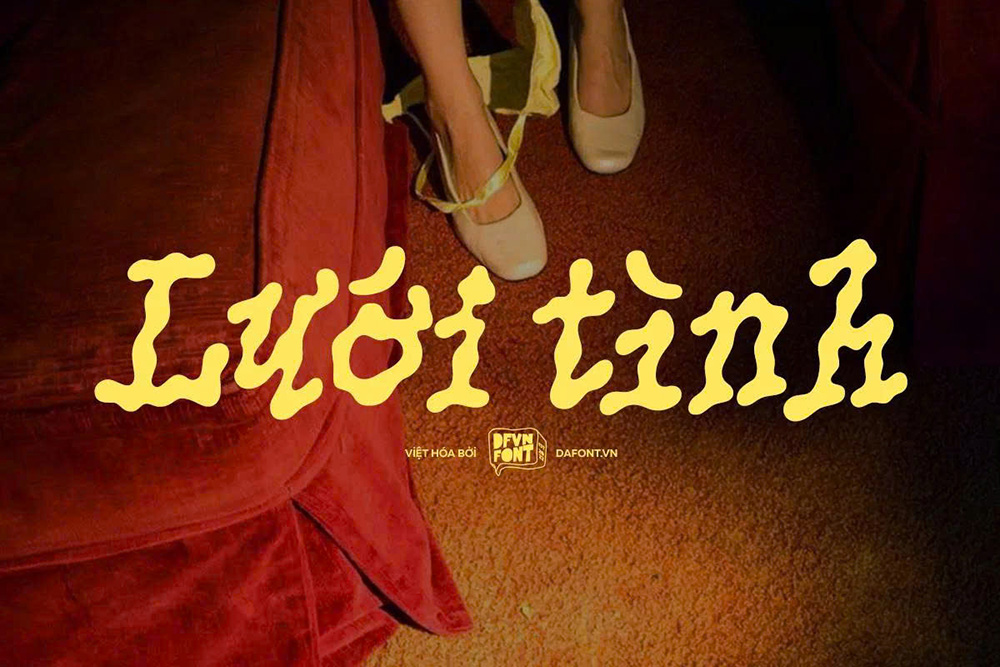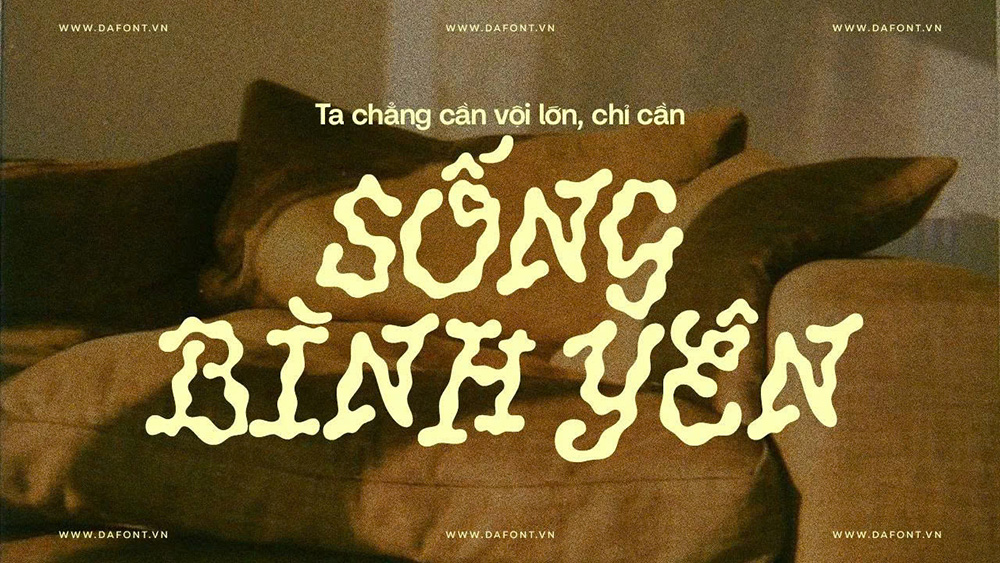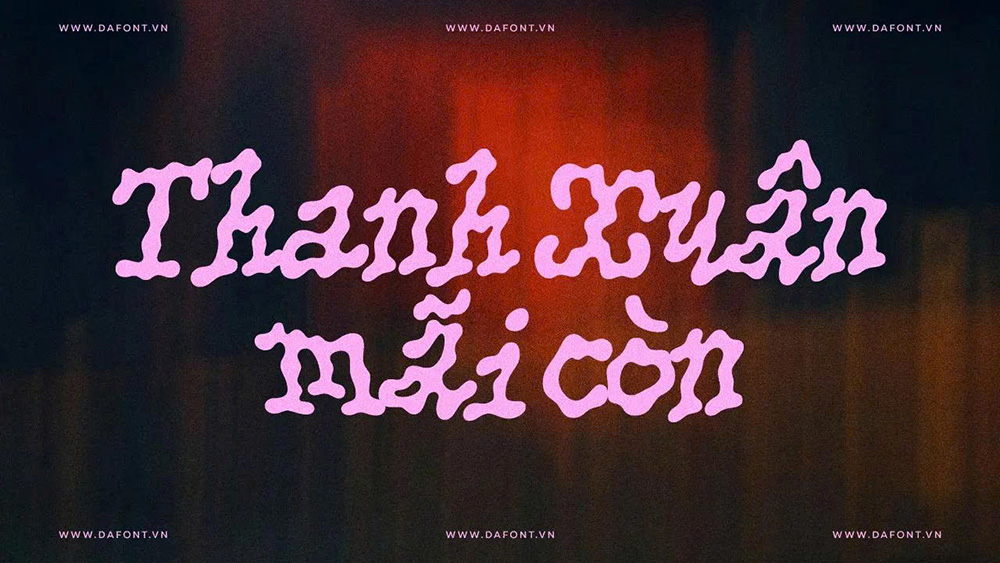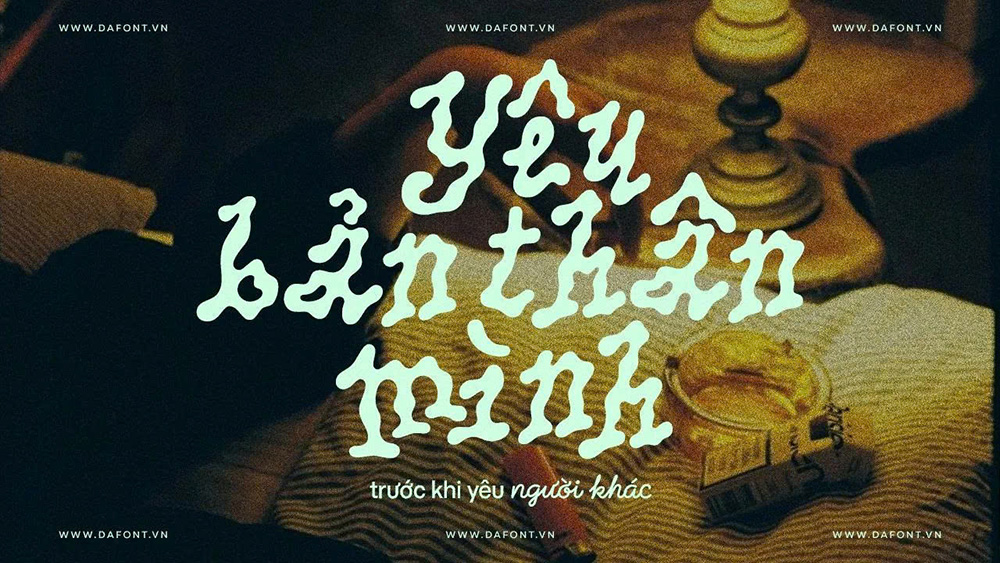
Font Việt Hóa - PicNic Mang Phong Cách Ngẫu Hứng và Uyển Chuyển
Picnic font là một kiểu chữ serif mang cảm hứng tự nhiên, được sinh ra từ những quan sát tinh tế về thế giới xung quanh: quỹ đạo mềm mại của giọt nước lăn trên tấm vải dầu, bóng lá cây đổ xuống thảm cỏ, hay hành trình tỉ mỉ của một chú kiến tìm đến miếng dưa hấu đỏ mọng.
Mỗi chi tiết đều góp phần tái hiện trải nghiệm giác quan đầy thi vị của một buổi picnic cùng bạn bè – nơi sự hoang dã, thơ mộng và bình yên hòa quyện để tạo nên một phong cách chữ vừa tự do vừa đậm chất “bucolic” – nét đẹp mộc mạc của đồng quê.
PicNic font nổi bật với thiết kế hữu cơ (organic typeface), không theo lối cứng nhắc mà tràn đầy sự linh hoạt và vui tươi. Dưới đây là những tính năng chính khiến font chữ PicNic trở thành lựa chọn yêu thích của các designer:
- Ligatures ngữ cảnh và Inclusive ligatures: Font tự động thay thế midpoint (dấu chấm giữa) bằng các ligatures thông minh, tạo nên dòng chữ mượt mà và tự nhiên. Ví dụ: Các ligatures cơ bản như “bb”, “ct”, “fl”, “ques”, “rss”; ligatures viết hoa như “C FU”, “ŒU”; và inclusive ligatures đặc biệt cho từ như “ICE”, “ices”, “é”, “i·e”.
- Một style duy nhất: Với 1 kiểu regular, font dễ dàng kết hợp trong các dự án đa dạng, từ in ấn đến digital.
- OpenType features: Hỗ trợ đầy đủ ligatures, diacritics (dấu phụ), giúp font hoạt động mượt mà trên các phần mềm như Adobe Illustrator, InDesign hay Figma.
- Thiết kế hữu cơ (Organic typeface): Các đường nét mềm mại, gợi cảm giác tự nhiên, lý tưởng cho nội dung mang tính kể chuyện hoặc cảm xúc.
Ứng dụng và gợi ý sử dụng trong thiết kế
Khi nào nên chọn DFVN PicNic
- Thiết kế thương hiệu mang hướng tự nhiên, handmade, organic: vì chất lượng chữ mềm mại và hơi “ngẫu hứng” nên rất phù hợp.
- Bao bì sản phẩm, nhãn mác, poster sự kiện ngoài trời, flyer picnic, café sân vườn, lifestyle…
- Tiêu đề (heading) hoặc tên thương hiệu, vì chỉ có một style nên không khuyến nghị sử dụng cho văn bản dài chỉn chu.